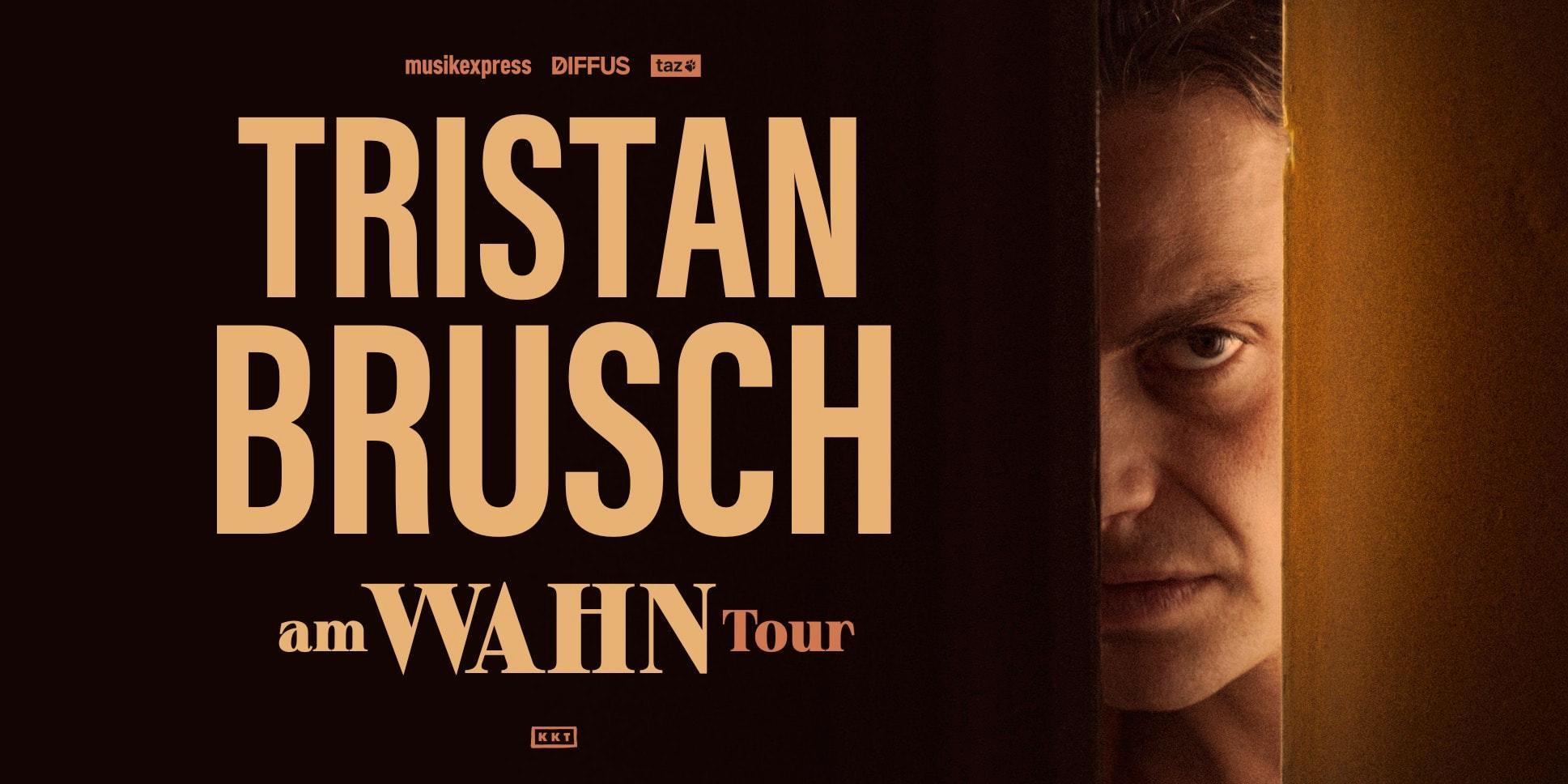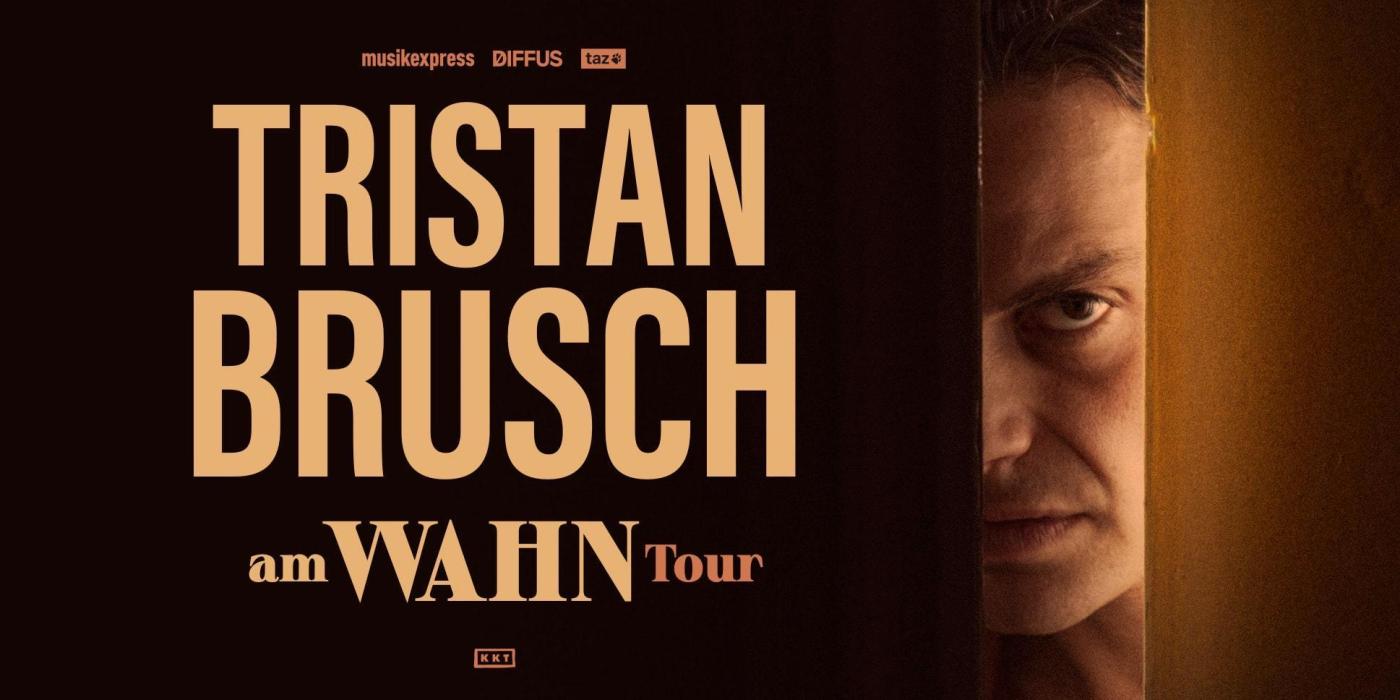
Suche den Namen dieser Schrift vom Album-Cover und Tourwerbung von Tristan Bruschs "Am Wahn" (2023)
Ich bin aus Recherchezwecken auf der Suche nach dem Namen der Schrift, in der die Worte "am WAHN Tour" gesetzt sind. Am ehesten sieht sie nach der Denver Serial Black aus, aber die ist es nicht (z.B. ist das kleine "a" dort anders). Klar, vielleicht handelt es sich um ein eigens erstelltes Design, aber da die Worte "TRISTAN BRUSCH" meiner Einschätzung nach in der allgemein verfügbaren Acumin Pro ExtraCondensed Bold gesetzt sein dürften, dachte ich, dass es sich bei "am WAHN Tour" evtl. auch um eine existierende Schrift handelt.